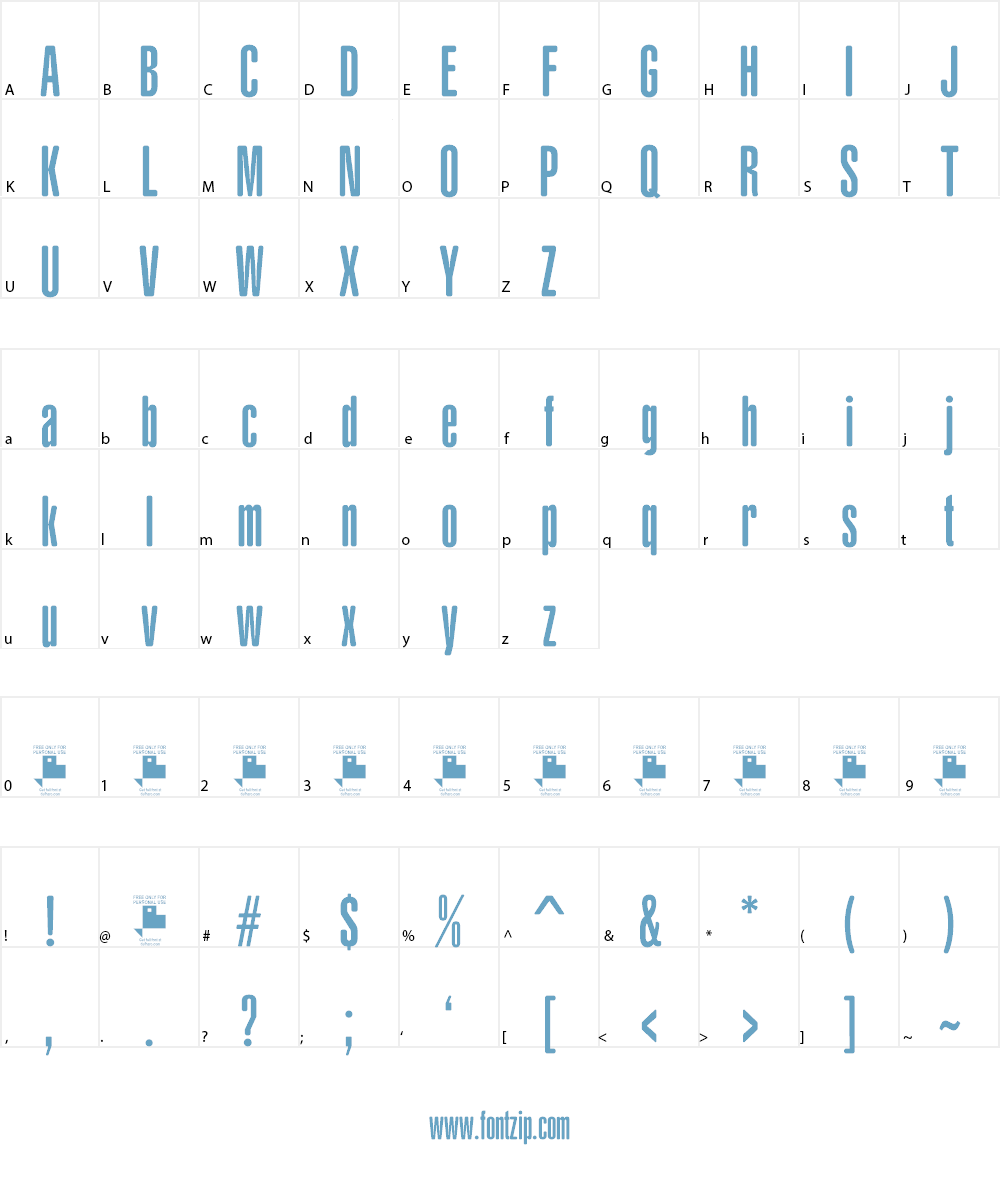
Yacarena Ultra es un proyecto tipográfico surgido de mi necesidad redundante de disponer de una fuente muy condensada para ciertos trabajos de diseño gráfico donde la cantidad de texto en grandes títulos complican la composición.
Yacarena Ultra is a typographic project emerged from my redundant to have a very condensed font for some graphic design work where the amount of text in large titles need complicated composition.